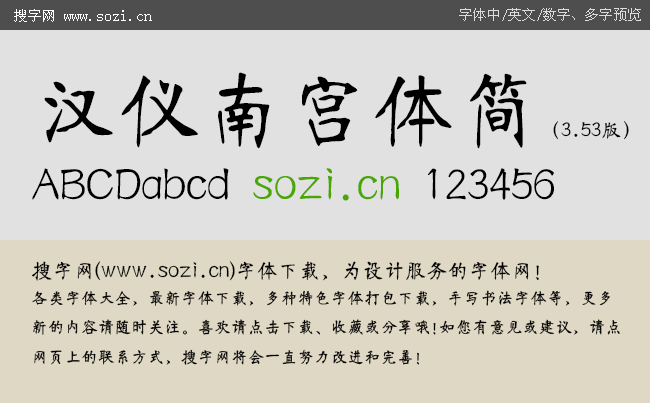
漢儀南宮體簡
搜字網(wǎng)給大家提供一款漢儀漢儀南宮體簡中文藝術(shù)字體下載。內(nèi)圓外方,即筆畫轉(zhuǎn)折處內(nèi)呈圓弧而外為方角,橫豎相接處有“焊接”的藝術(shù)效果和金石的韻味。其化北碑為己用,將北碑的扁方體勢變化成唐楷的縱方體勢,將篆、隸、魏碑及唐楷的運筆方法融為一體,自成一家,是一套融古創(chuàng)新的字體。適合正文、標題、廣告設(shè)計使用。